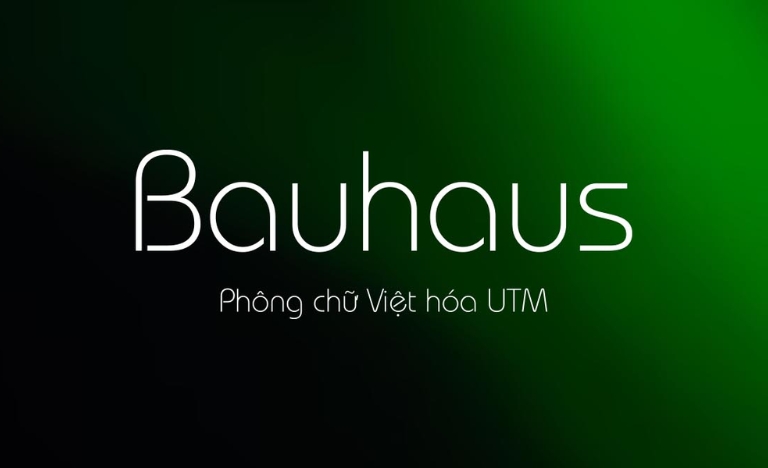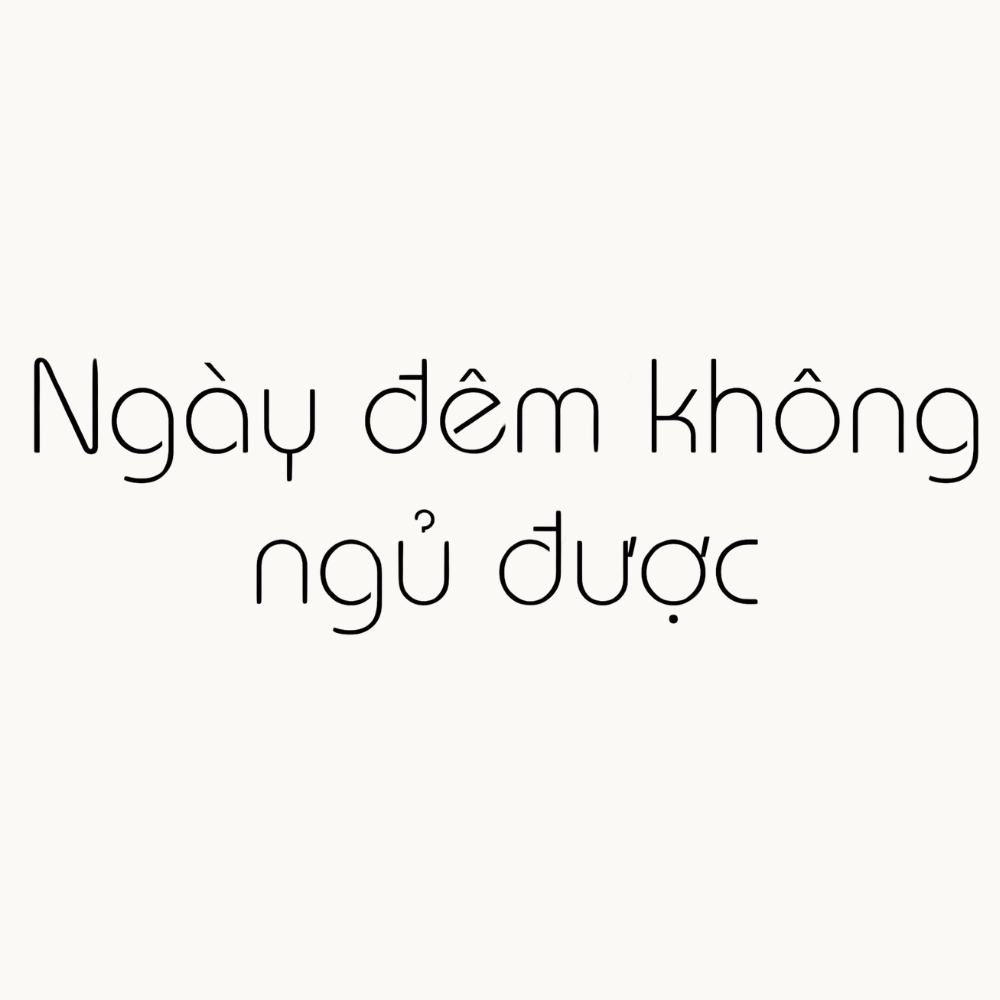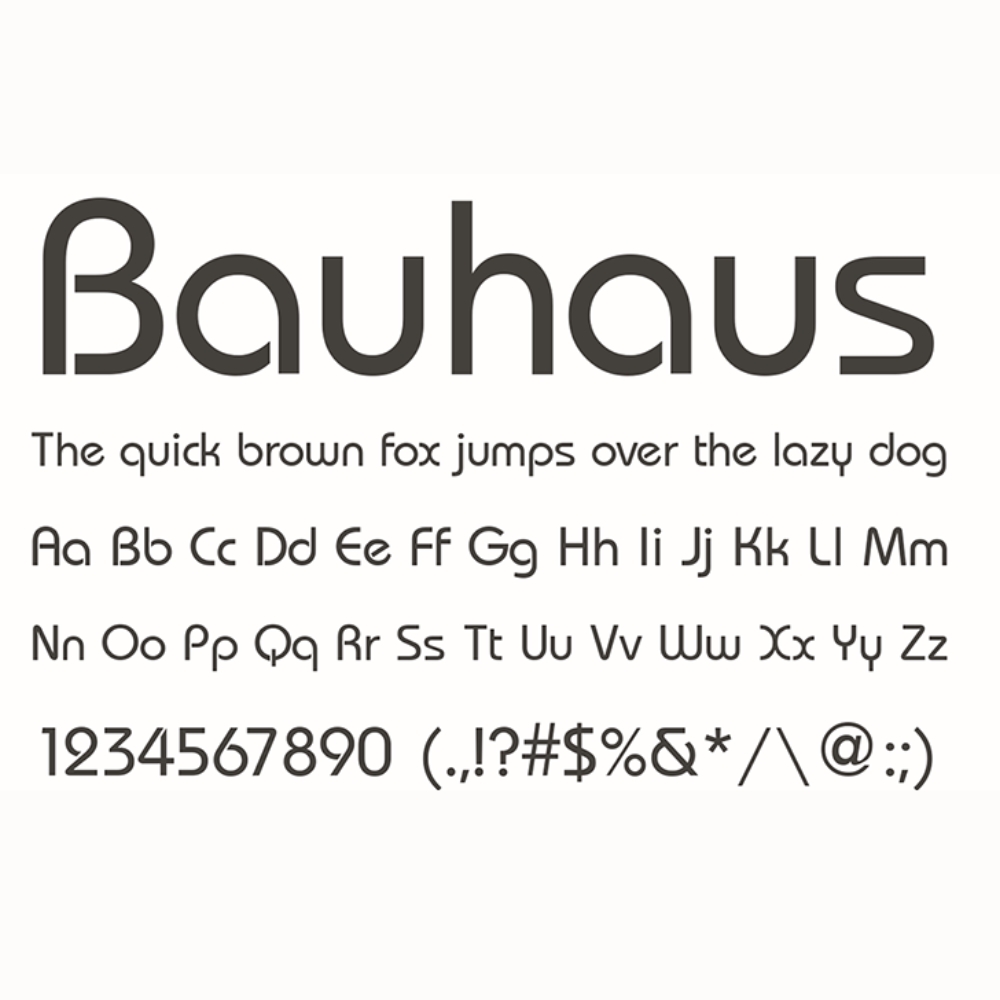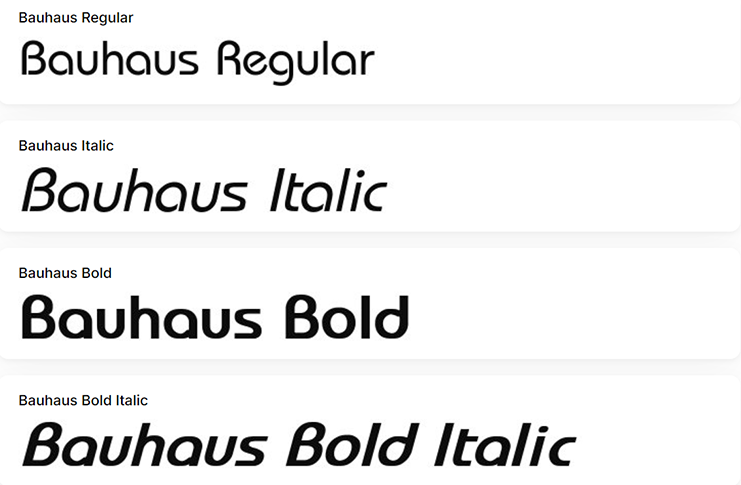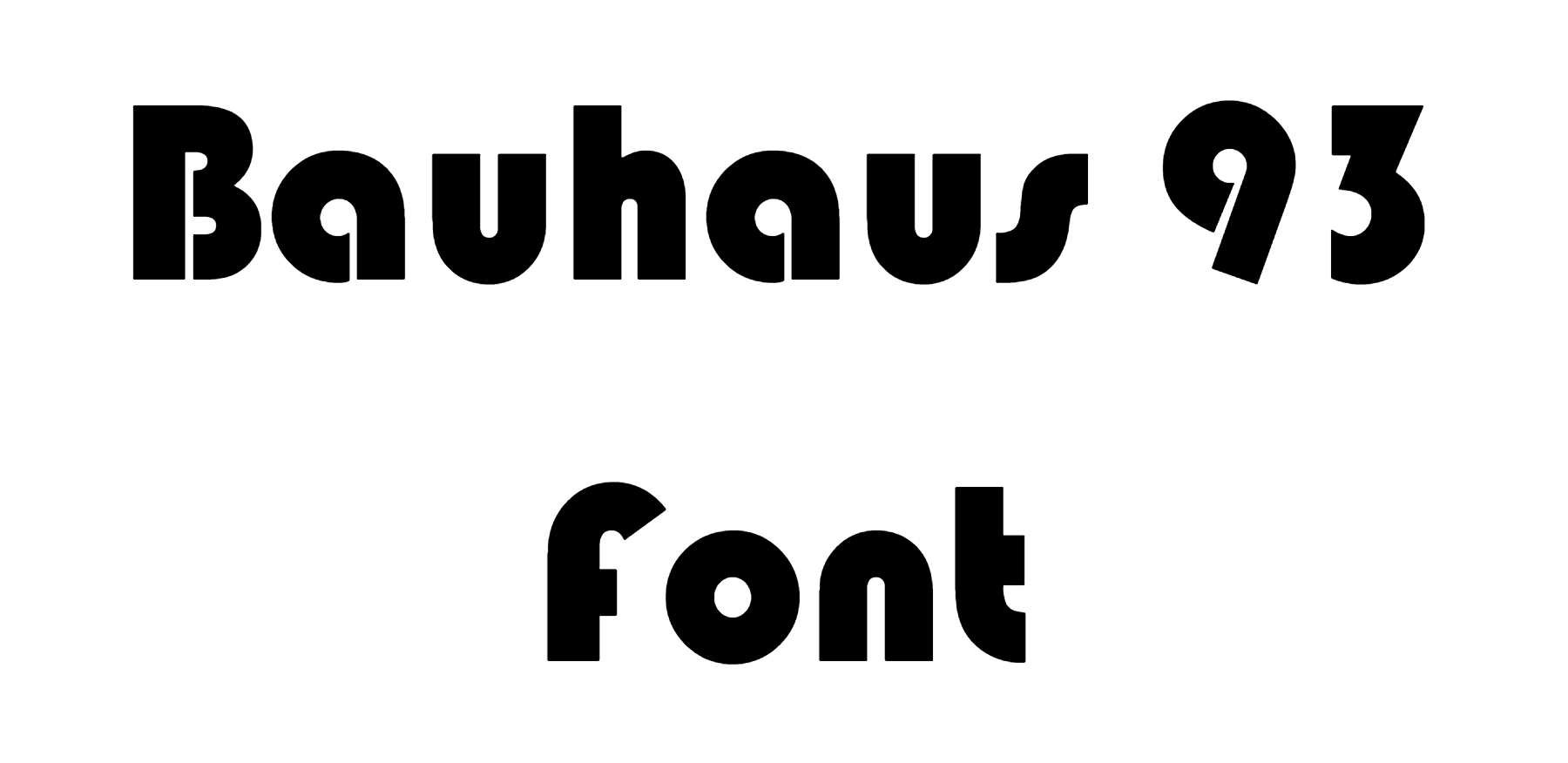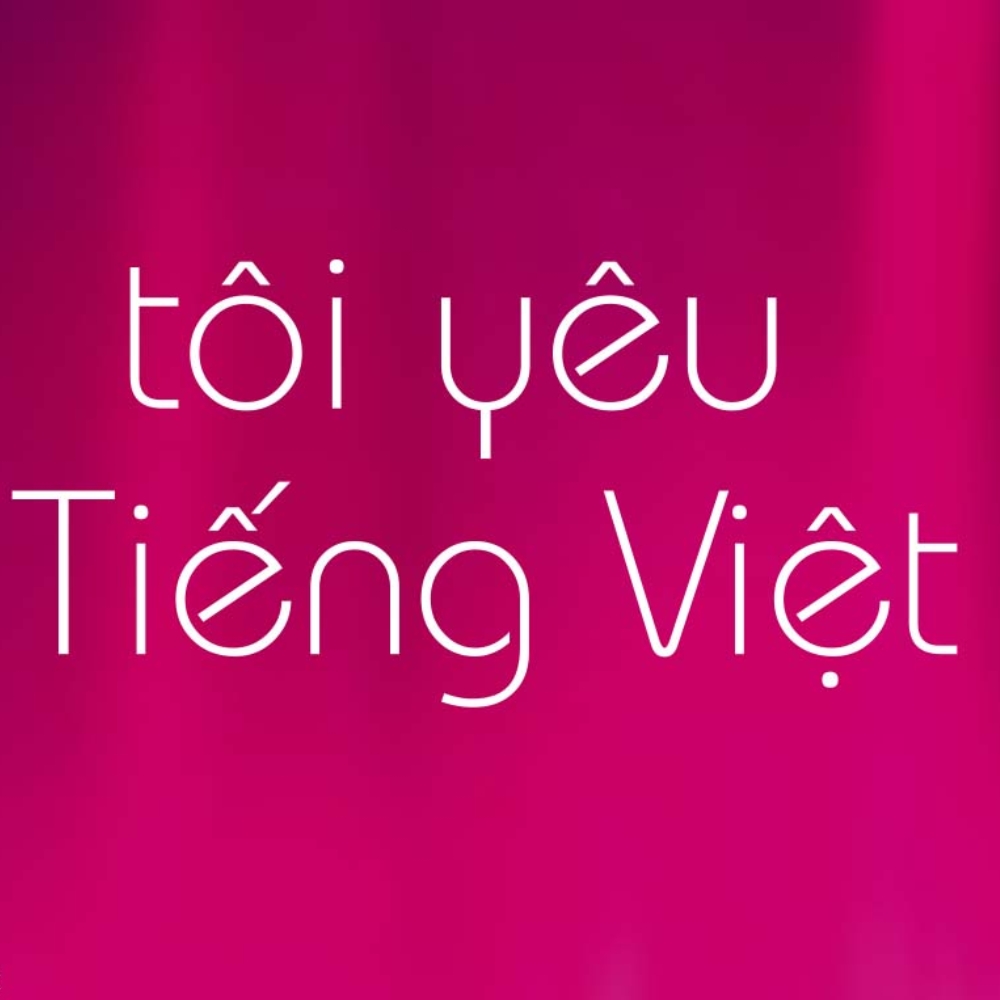
Bauhaus không chỉ là tên của một trường phái nghệ thuật lừng danh mà còn đại diện cho triết lý thiết kế “công năng đi trước thẩm mỹ”. Các bộ font Bauhaus Việt hóa mang trong mình tinh thần tối giản, sử dụng những đường nét hình học cơ bản để tạo nên sự hiện đại và phá cách.
Đặc trưng hình học của font Bauhaus Việt hóa trong thiết kế hiện đại
Điểm thu hút của dòng font này chính là cấu trúc dựa trên các khối hình cơ bản như hình tròn, đường thẳng và các góc bo mịn màng. Font Bauhaus 93 Việt hóa là một trong những phiên bản phổ biến, nổi bật với các nét chữ dày, thông thoáng và loại bỏ hoàn toàn các chi tiết rườm rà. Việc tối ưu hóa bộ dấu tiếng Việt giúp các ký tự đặc biệt được đặt ở vị trí cân đối, duy trì nhịp điệu hình học xuyên suốt của bộ chữ gốc mà không gây hiện tượng lỗi hiển thị văn bản.
Sự ổn định của font chữ Bauhaus còn thể hiện qua khả năng tạo dựng hình ảnh chuyên nghiệp và tư duy logic. Những đường uốn lượn mượt mà kết hợp cùng các khoảng hở tinh tế giúp văn bản trở nên nổi bật, đặc biệt phù hợp với các thiết kế hướng đến tương lai hoặc phong cách Industrial. Đây là phương án hiệu quả để truyền tải các thông điệp về sự gọn gàng, tính ứng dụng và gu thẩm mỹ tối giản cho mọi dự án sáng tạo.
| Phân loại phong cách | Geometric Sans-serif / Bauhaus Style |
| Số lượng biến thể | Đầy đủ kiểu Light, Medium, Bold, Bauhaus 93 |
| Mục đích phù hợp | Logo, Tiêu đề, Poster, Hồ sơ dự án kiến trúc |
Gợi ý phối hợp: Font Bauhaus có cá tính hình học rất mạnh. Bạn nên phối hợp chúng cùng các font không chân tối giản khác cho phần nội dung chi tiết để tạo ra sự cân bằng thị giác, giúp người xem dễ dàng tập trung vào những thông tin cốt lõi của bản thiết kế.
Nhờ vẻ ngoài mang tính biểu tượng và sự mạch lạc, bộ font chữ này mang lại giá trị thực tế khi được đưa vào thực tế trang trí và quảng bá công trình hiện đại:
- Bảng hiệu cho văn phòng và nhà lắp ghép hiện đại: Những nét chữ tròn trịa của Bauhaus rất ăn ý khi xuất hiện trên chất liệu kim loại hoặc mica gương tại các khu văn phòng container. Font chữ này giúp công trình toát lên vẻ ngoài chuyên nghiệp và tư duy thiết kế thông minh.
- Thiết kế bộ nhận diện thương hiệu nội thất: Sử dụng font chữ này giúp logo và các ấn phẩm truyền thông mang đậm phong cách kiến trúc hiện đại, dễ dàng tạo được sự kết nối với khách hàng yêu thích lối sống tối giản.
- Trang trí không gian nghệ thuật: Bạn có thể dùng font này để làm decal dán tường hoặc cắt chữ nổi trang trí tại phòng khách nhà lắp ghép nhằm tạo điểm nhấn đầy thẩm mỹ và khơi gợi cảm hứng sáng tạo.
Để khai thác hiệu quả vẻ đẹp của dòng font Sans-serif đặc trưng này mà không làm ảnh hưởng đến thẩm mỹ chung, người thiết kế nên lưu tâm một số kinh nghiệm sau:
- Lựa chọn độ đậm phù hợp: Font Bauhaus Bold Việt hóa sẽ tạo ấn tượng mạnh cho các tiêu đề chính, trong khi font Bauhaus Medium Việt hóa mang lại sự hài hòa hơn cho các đề mục phụ hoặc các câu slogan ngắn.
- Kiểm soát khoảng cách dòng: Do cấu trúc chữ có xu hướng tròn và dàn ngang, bạn nên thiết lập khoảng cách dòng thoáng một chút để văn bản không bị bết dính, giúp tổng thể bản thiết kế trở nên minh bạch hơn.
- Hạn chế dùng cho văn bản dài: Bauhaus là dòng font Display, vì vậy bạn chỉ nên sử dụng cho tiêu đề hoặc các đoạn nội dung ngắn. Sử dụng cho đoạn văn bản dài sẽ gây mỏi mắt và làm giảm hiệu quả truyền tải thông tin.